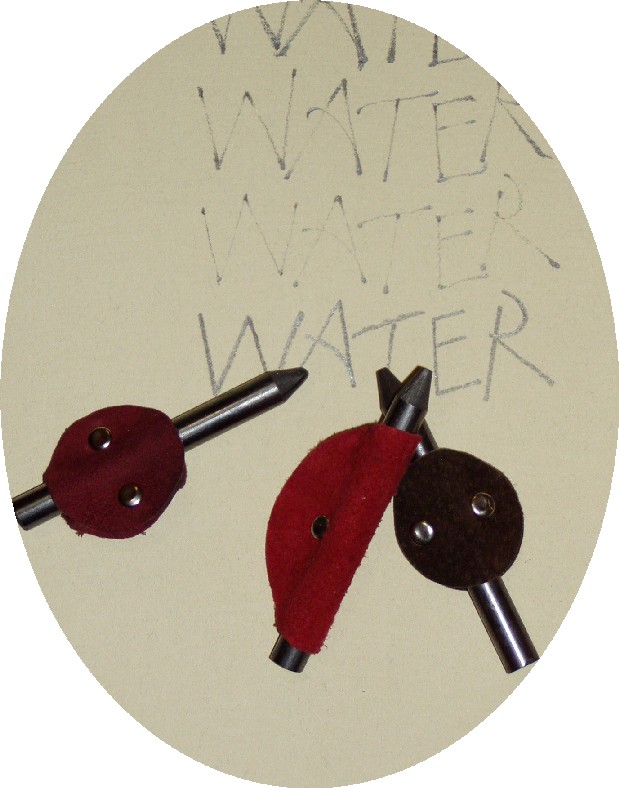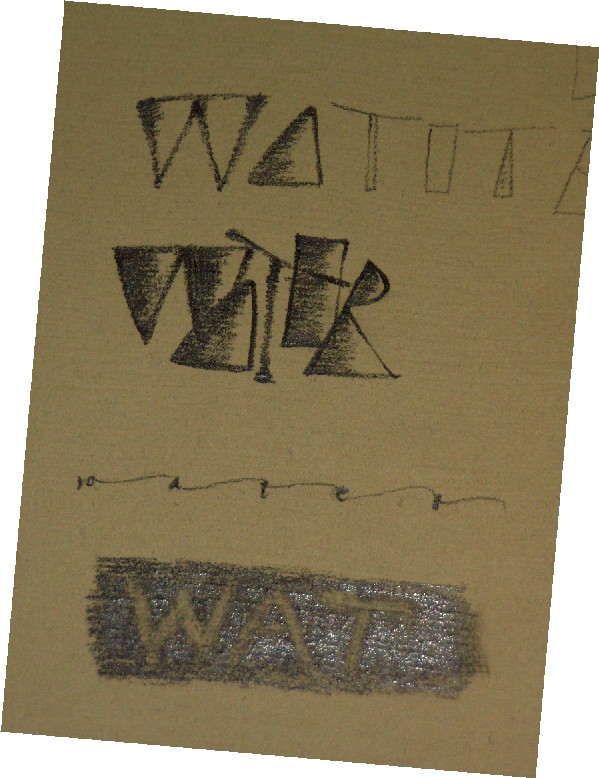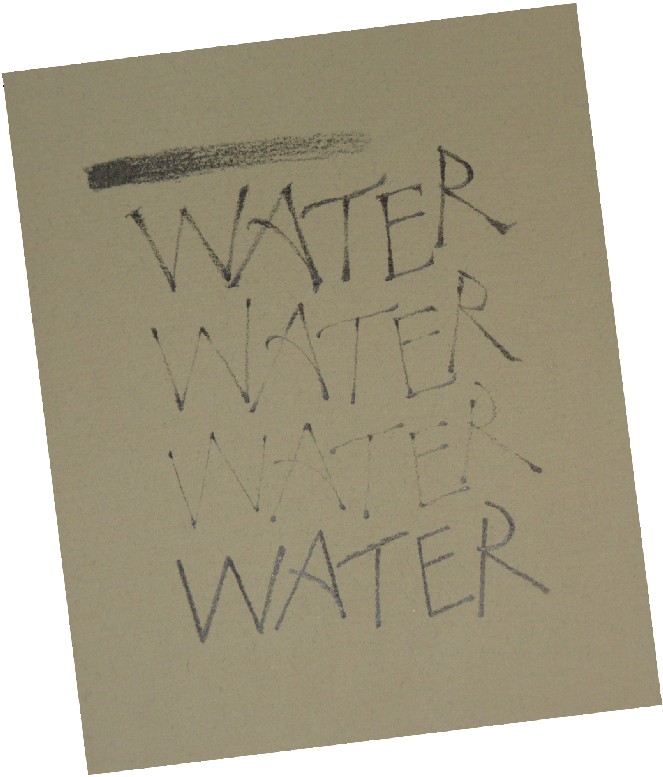
スパッタリング
下地を作る時のテクニックでよく使われるスパッタリング。皆さんは何を使いますか?
歯ブラシ派?それとも金網派?
私はこのスパッタリング用のツールを使います。名前は「?」わかりません・・・アメリカ製でKemper Toolと書いてあります。
アメリカの道具にはとても不思議な物がたくさんありますが、これはとても優れモノです。ブラシの横に針金が付いていて、まわしたブラシがそれに当たって絵の具が飛ぶのです。歯ブラシではここまで細かなスパッタリングにはなりません。非常に細かくピシピシと絵の具が飛んでくれます。
いろいろな色を重ねて使うと、ホラこんなに綺麗。乾いてから次の色をやっていくのがコツです。楽しくて、やり続けてしまいますね。
非常に小さな点が飛びますので、マスキングをしても、白ヌキがしっかり出来ます。
この道具には、ブラシの部分がもっと長いのもあって(もちろん持ってます!)広い部分をやるにはとても便利です。
小菊集
友人の義理の祖母、せいさんが亡くなった後、せいさんのお部屋を片付けていたら、生前、ノートに書きためておいた俳句や和歌が出て来たそうです。
生きている頃、そんな趣味があった事は家族の誰も知らなかったそうで、皆一様に驚きました。そして息子さんがこれらをワープロで打って簡単な小菊集を作り、親戚へ配りました。
カバーはこれはなんという物なのでしょうか、穴の開いた薄いメタルで(一体どこでこういう物をみつけるのか!?)そこにトレーシングペーパーが重なっています。バインディングは、メタルに開いている穴を上手に使ってとじてあります。
固いマテリアルなので、ちゃんと開くのかな?と思ったら、そこはプロの手仕事!ページの部分と本体はトレーシングペーパーでつながっているので、ハードな外側なのに綺麗に平らに開きくことができるのです。
半透明な柔らかさとシルバーなメタリック。
作家からのメッセージに、「本を手にした時にせいさんの声が聞こえるよう、また歌声を閉じ込めないよう、透明性の高いトレーシングペーパーと穴のあいた金属を使った」と書いてあります。
こうして素晴らしい作品となった小菊集、友人に6月に入ったら渡す事になっています。喜ぶ顔が早く見たい!と今から楽しみにしているmojitor-sでした。
福永由美子さんの個展
小雨に濡れ、水玉をキラキラさせて、さながらタペストリーのようなバラの群生が出迎えてくれる…ここはイギリス風の建物とガーデンのあるCLAREです。
土曜日は、この美しい建物の中で行われている「福永由美子作品展」を訪れました。
アンティークの家具に囲まれて、そこに以前からあったかのように自然な落ち着きで福永さんの作品はありました。
今回は植物が中心…しかも多肉植物が主役です。小さな者達が福永さんの作品の中ではなんて表情豊かなんでしょう〜。彼女の手によって描かれた植物達は磁器の中でも生き生きとしています。モデルになった本物君たちも元気いっぱいに…ちょっとおすましして並んでいました〜。多肉植物ってこんな表情していたんですね〜。とっても素敵でした!
もう手にとって眺めたら自分の手元に置いておきたいという衝動にかられるものばかりです!福永さんの世界には本当にため息がでます…。繊細な文字も本当に素敵です。
今回特に感激したのは、以前ご紹介した福永さんのステーショナリーに描かれていた「葉っぱ」の原画があったことです〜。生きててよかった〜と真剣に思いました!
テーブルの上の食器達も葉っぱでいっぱい飾られています!こんなお皿でお食事したら…さぞかし優雅な時を過ごせるでしょうねぇ…。
賞を取った絵付けの食器も展示してあり、見ごたえありました。
月光荘の8B君
「えっ?これ全部芯?なんか魅力的…」しかも指が汚れないようにバックスキン(しかもカラフル)でカバーしてあります。
聞くところによれば、このカバーは月光荘のお稽古バッグにも出てきましたフォルンマークを作るときの端切れを利用しているそうです。なので端切れが出ない限り、この衣を身に着けた8B君も店頭に顔を出さないとか…。
ちょうどその日は8B君たちが可愛い衣をまとって店頭に並んでいました。ラッキーでした。
全部芯なので、少し重みがあって持ちやすいし、コントロールがしやすいです。8Bという性格上薄い色から濃い色までグラデーションが豊富に作れます。
私はカリ文字を鉛筆系で書くのも大好きです。ちょっとデッサン風、ドローイング風に書いてみました〜。
普通に書くときもポイントに圧をかけて、それ以外は軽く書いて(力を抜く感じ)…この繰り返しで書いていくと、実際のペンで書くときにも同じようなりズムで書くことが出来るようになります。
8B君で書くと線だけでも楽しめるし、面構成でも遊べます。インクでは出来ない表情をつけることが出来ますね…。鉛筆のようにすぐに芯が潰れていくこともないし、手の感触がそのまま伝わります。
次回はダブルペンシルで遊ぼうかな…と思います〜。
アンパーサンド
調べてみたら、この名前は「and per se and」というフレーズから生まれたのだそうです。これは「この記号(&)はそれ自体がandを意味する」という意味でなんですって。要するに「"&"は、だからね、ANDなんですよー」って事らしい。
きちんと座って先生の指し示す文字に従って、子供たちが暗唱する場面を想像すると、とても面白いですね!
新しい書体を作るとき、デザイナーはアンパーサンドの文字に最も芸術的なセンスを注ぎ込む、と言われています。
いつも同じような&を書いているので、16世紀のマスターたちのアンパーサンドを参考に、ちょっと遊びの入ったアンパーサンドもいいかもね。
タンポポの旅
家の近所に空き地があって、そこはついこの前までタンポポでいっぱいでした。
地際で咲いている黄色い花もかわいいけれど、風に「吹いて、吹いて」と言わんばかりに背を伸ばしているタンポポの綿毛も健気にがんばっているなあと、散歩のときについにっこり。
ここのところ雨が続いて、綿毛もすっかり落ちてしまったのではないかしら、と思ってその話を子どもにしたところ・・・
「タンポポの綿毛は湿った日には、すぼんでいるんだよ」
学校で習ったそうで、知識を披露してくれました。あらー、そうなの?
タンポポの花は咲き終わったあと、ぐったりと倒れているがそれは枯れたのではなくて
種に栄養を送っていること。そしてできるだけ遠くに飛べるように軸をぐんぐん伸ばしていくこと。
そうやって、晴れた乾いた日に落下傘となって飛んでいくのだそうです。へえ、でしたー。
四色問題
以前新聞で、代表的な数学の難問の一つがロシアの数学者の手によって解決されたらしい・・という記事を読みました。
なんでも未解決な問題はいろいろあるらしく、その中の何が解決されたか忘れてしまいましたが(っていうか、もともと何が問題なのかもサッパリわからん!)その記事に、解決済みの問題も載っていました。
カリをしていると、ライトテーブルは必需品ではあります。しかし、本気で買おうとするとお高い商品なので…ウウッ…手が届きません!日中はお日様の力を借りて、窓ガラスにくっつけ書いたりもしますが、垂直に写すのは結構疲れます…。
以前、天才大工Wさんが蛍光灯を改良したこんなライトを作ってくれました〜。これは本当に便利であります。懐中電灯だと光の面積が小さいので、大きい面で写すときに困っていましたが、これだとわりと長い面で光を捉えることができます。
恥ずかしながら…私の場合、傾斜板の高さはそこら辺にある辞書で調整しています。世のカリ人のみなさんは、もっとちゃんとした傾斜板を使っているのでしょうが…。
ライトテーブルとして使用する場合は…ちなみにこの傾斜板はアクリル板をカットしてもらったものですから光は通ります…下にWさん作の蛍光灯を置きます。すると簡単、簡易式ライトテーブルの出来上がり!です。
…そんでもって、こうして、お仕事してます〜。
ほらねぇ〜。ライトテーブルみたいな感じでしょう〜?普通に売っているライトテーブルよりはるかに安い便利お道具です。
Wさん…あなたが器用でよかった…。
でも、最初は黒い紙も光が通ると思って乗せてみたら…通るわけないじゃん!